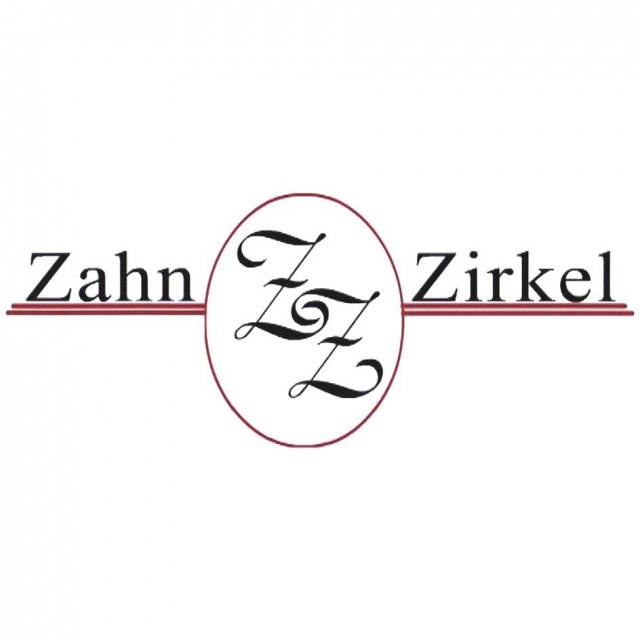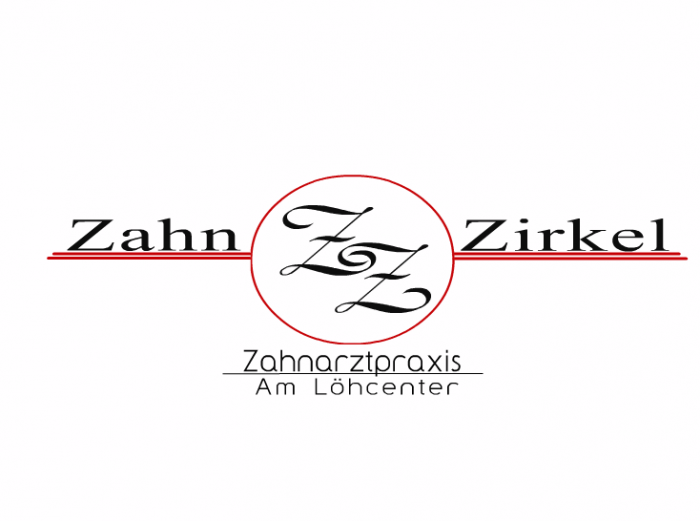
Schlimmer geht´s nimmer, sorry aber das Logo habe nicht ich gemacht.
Die oberen Beiden sind Times und Typo Upwright, aber laaaaaang gezogen!!
Kennt jemand die unteren Beiden?